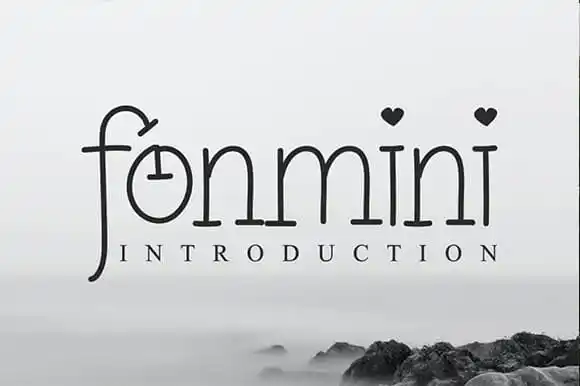
A Fonmini Serif Font é uma escolha perfeita para quem busca estilo clássico e elegância nas criações digitais. Este tipo-fonte serif oferece a combinação perfeita de simetria e detalhes, projetado para destacar em ambientes que requerem um toque especial de sofisticação, desde embalagens até logotipos no Instagram. Seja para adicionar um toque único aos seus posts nas redes sociais ou ao design de suas invitativas casamentarias, a Fonmini Serif Font oferece o ideal para qualquer projeto que busque uma pitada de riqueza visual. Suas linhas serifadas são perfeitas para criar identidades visuais memoráveis e destacar produtos e conteúdos, garantindo um toque cuidadosamente pensado e atemporal em cada projeto. Não espere mais – a adição da Fonmini Serif Font ao seu arsenal de ferramentas digitais pode transformar qualquer documento ou arte digital no qual você esteja trabalhando.